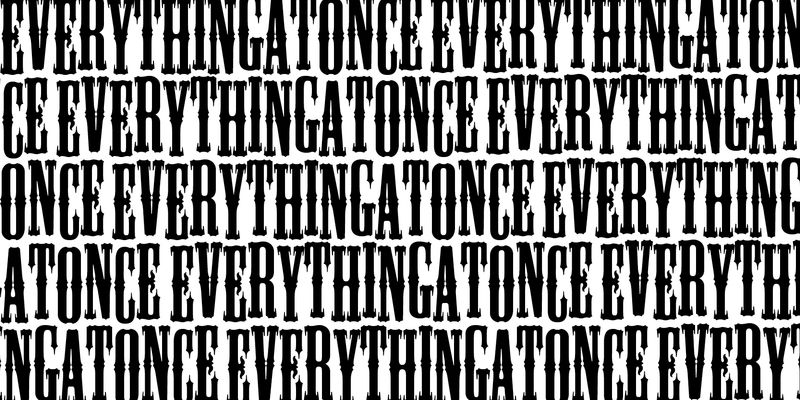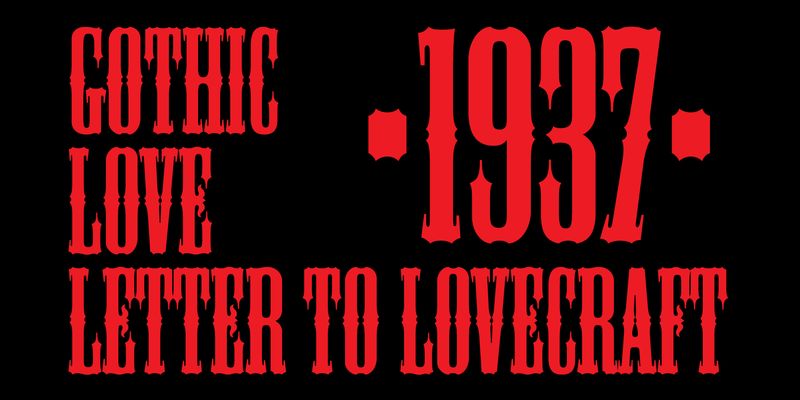
Mesquite ist eine Adobe Originals-Schrift, die 1990 von Joy Redick für Adobe Systems als Teil der Adobe Wood Type-Serie entworfen wurde.
Das Adobe Originals-Programm wurde 1989 als hauseigene Foundry bei Adobe gegründet, um Originalschriften von beispielhafter Designqualität, technischer Treue und ästhetischer Langlebigkeit zu entwickeln.
Heute besteht die Aufgabe des Type-Teams darin, anspruchsvolle und sogar experimentelle Schriften zu entwickeln, die die Möglichkeiten von Design und Technologie ausloten. Die Schriftarten, die als Adobe Originals veröffentlicht werden, sind das Ergebnis jahrelanger Arbeit und Studien und gelten als Industriestandard für den Ehrgeiz und die Qualität ihrer Entwicklung.